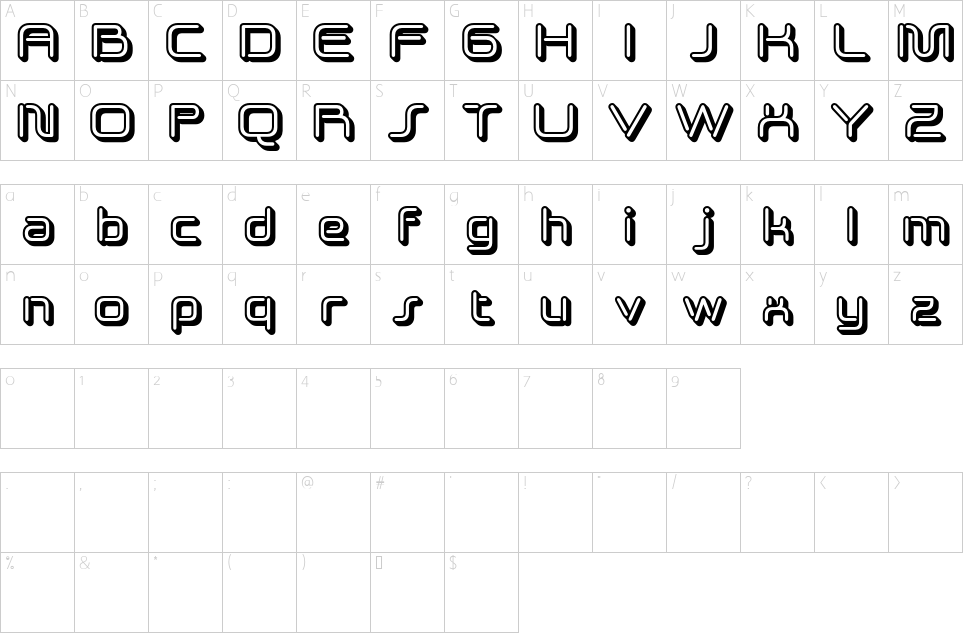
A Devano é uma fonte elegante e versátil criada pela Craft Supply Co. Ela combina perfeitamente para textos de layout e design editorial, oferecendo um conjunto variado de caracteres que a tornam perfeita tanto para textos legíveis quanto para elementos gráficos mais elaborados. Desenvolvida para atender uma ampla variedade de necessidades, esta fonte foi baixada 112 vezes pela comunidade de designers e criativos que valorizam o equilíbrio entre aparência e funcionalidade. Para aqueles que buscam qualidade em sua base gráfica sem comprometer a experiência visual ou se tornarem dependentes dos arquivos de fonte pagos, a Devano é uma escolha inteligente. Descubra por si mesmo como essa fonte pode complementar seu trabalho.